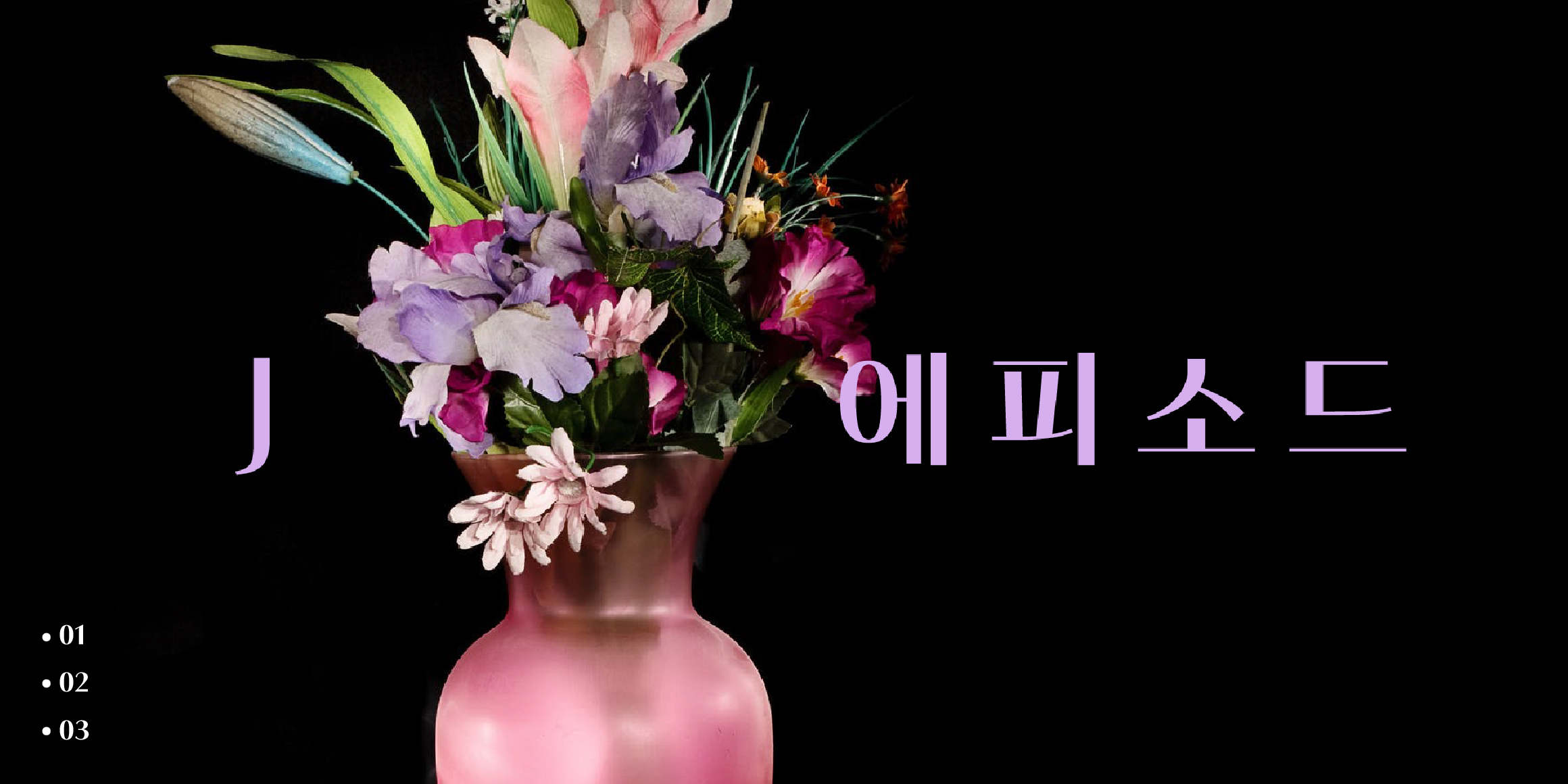
우주와 미래를 그리는 SF 폰트 추천
이번 큐레이션에서는 SF 장르에서 영감을 얻은 폰트들을 소개합니다.
우주 배경, 디지털 인터페이스를 표현할 폰트를 찾는다면 주목해 주세요!
To Infinity and Beyond! 🛸
무한한 공간 저 너머로!
우주와 미래를 다룬 SF 영화나 드라마에서는 미래적인 느낌의 타이포그래피가 중요한데요.
이번 큐레이션에서는 SF 장르에서 영감을 얻은 폰트들을 소개합니다.
우주선 조종실, 디지털 인터페이스, 인공지능의 음성 메시지 자막까지.
레트로 퓨처리즘 분위기를 완성하는 폰트들을 만나보세요!
#01. 우주와 맞닿은 한글
SF 장르에서 자주 보이는 ‘레트로 퓨처리즘’ 감성을 한글로도 표현한다면 어떤 모습일까요? 기계처럼 정밀한 구조와 과거에서 온 듯한 디자인이 공존하는 이 폰트들은, 마치 우주복을 입은 한글처럼 느껴져요. SF 분위기를 연출하고 싶은 포스터나 표지에 사용할 수 있는 이 조합, 꼭 눈여겨보세요!
SD 코스모
• 파란색 우주 배경 위에 네온 사인 효과가 적용된 굵은 한글 타이틀 그래픽: 레트로 퓨처리즘. FONT: SD 코스모
• 파란색 우주 배경의 굵은 텍스트: 코스모스(cosmos) 우주관. FONT: SD 코스모
• 우주 배경 위에 두 단으로 나열된 SF 영화 제목 리스트. 터미네이터, 블레이드러너, 에반게리온, 스타트렉 등. FONT: SD 코스모
「SD 코스모」는 ‘레트로 퓨처리즘’이라는 키워드로 제작된, 이름부터 우주와 맞닿아 있는 폰트입니다. 각진 형태와 대각선으로 커팅된 획이 만들어내는 독특한 구조로 기계적이되 정적인 느낌보다는 역동적인 인상을 가지고 있어요. 특히 오픈타입 피처 기능으로 단어의 첫 자와 마지막 자를 대체하면, 타이틀을 더 매력적으로 디자인할 수 있답니다. 큰 사이즈에서 매력이 더 잘 드러나는 폰트로, 포스터나 오프닝 타이틀용으로 추천합니다!
J에피소드_플래시백
• 달 표면 배경의 텍스트: 암스트롱, FONT: J에피소드 플래시백
• 달 표면 배경의 영문 텍스트: 암스트롱의 달 착륙 관련 인용구. FONT: J에피소드 플래시백
• 검은 배경과 녹색 달 그래픽 위에 배치된 폰트 적용 예시. J에피소드 플래시백 02, 03 서체 비교 예시
「J에피소드_플래시백」은 직지소프트의 J에피소드 패밀리의 두 번째 시리즈 폰트입니다. 기존 J에피소드 시리즈의 느낌을 이어가되, ‘과거와 맞닿은 미래’라는 컨셉 아래 획 대비를 반전시켜 완전히 상반된 인상을 보여줍니다. 반전된 획이 만들어내는 묘한 이질감이 SF 장르의 감성을 한층 살려주죠. 아날로그한 감성을 입힌 미래 배경이나 주제와 관련된 디자인에 에피소드 플래시백을 활용해 보세요!
HG코스모스
어두운 우주 배경에 붉은색 굵은 강조된 텍스트: 공간의 광막함과 시간의 영겁에서. FONT: HG코스모스
미래적인 분위기는 이런 디테일에서 나오는 걸까요? 역획대비(reverse-contrast)가 특징인 또 다른 디스플레이 폰트, 「HG코스모스」 입니다. 기본 구조와 형태는 꽉찬 네모꼴의 단단한 모듈을 가지고 있지만, 가로획과 세로획의 두께만 바꿔도 새로운 공간과 인상이 드러나죠. 직선적인 형태의 A 스타일과 곡선적인 형태의 B 스타일로 구성되어 있어, 차가움과 유려함 사이에서 원하는 스타일을 골라 사용해 보세요!
#02. 감각적인 미래의 언어
이번에는 SF 영화에서 자주 본 듯한 느낌의 영문 폰트들을 소개할게요. 어디선가 신비로운 빛을 내며 우주선 문이 열리면 등장할 것 같은 글자들이죠. 디지털 화면 위의 글자 같기도, 외계 생명체의 언어 같기도 한 이 폰트들만 있다면 SF 무드 완성은 시간 문제죠!
ABC Pareto
• Dinamo ABC Pareto 텍스트 그래픽, 전시 브로슈어와 엽서 목업 이미지 - 01
• Dinamo ABC Pareto 텍스트 그래픽, 전시 브로슈어와 엽서 목업 이미지 - 02
• Dinamo ABC Pareto 텍스트 그래픽, 전시 브로슈어와 엽서 목업 이미지 - 03
「ABC Pareto」는 이름만큼이나 다채로운 매력을 가진 폰트예요. 획 끝의 형태가 원형, 삼각형, 직사각형—세 가지 도형을 오가며 짜여진 글자로 독특한 성격을 자아냅니다. 마치 우주선이나 로켓의 일부분처럼 보이지 않나요? 폰트 하나만으로도 다양한 스타일을 표현할 수 있어서, 장면 전환이 많거나 복합적인 장르의 SF 콘텐츠에서 효과적으로 쓸 수 있어요!
TT Paplane Basic
TT Paplane 폰트의 적용 예시. 종이접기처럼 각진 형태의 알파벳, 숫자, 특수기호 디자인
「TT Paplane」은 종이비행기를 접어 만든 듯한, “paper plane”에서 이름을 따온 폰트예요. 종이처럼 평평하고 대비가 적은 Regular 스타일과, 독특한 역획대비가 적용된 Thin 2가지 스타일로 구성되어 있는데요. 특히 Thin은 영문 대문자가 소문자보다 확연히 좁은 비율로 구성되어 있어 인위적이고 기계적인 느낌을 살린 영상 자막이나 미래적인 디자인의 포스터에 활용하기 좋아요. 미디어아트 축제 <서울라이트 DDP 2025 여름> 포스터에 사용된 모습도 확인해보세요! (링크)
Bill Display
삼각형 도형을 기본으로 디자인된 기하학적 폰트 Bill Display 적용 예시
맥스 빌(Max Bill)의 레터링 작업을 기반으로 한 이 폰트는, 미니멀한 요소를 엣지 있게 활용한 「Bill Display」입니다. 트렌드를 따르기보다는, 시대를 초월하는 어휘를 구현하고자 한 폰트로 과거와 미래를 넘나드는 SF 장르에 아주 잘 어울리죠. 영문 대문자와 소문자 스타일이 분리되어 있어 원하는 형태를 골라 쓸 수도 있어요. 영화 오프닝 타이틀, 전시 포스터, 모션 그래픽 타이포그래피 등 미니멀한 무드가 필요한 프로젝트 어디든 효과적으로 활용해 보세요!
#03. 0과 1의 세계로
이 폰트들을 보고 있으면 마치 0과 1이 흘러다니는 데이터 세계에 들어온 듯한 느낌이에요. 픽셀이나 격자, 컬러로 디자인된 요소들 덕분에 보는 순간 배경이 ‘디지털’ 느낌으로 전환되죠. 고도로 발전한 미래의 기술이나 그래픽을 시각적으로 보여주고 싶을 때, 이 폰트만 사용해서 작업 시간까지 단축해보세요!
Shader color
레트로 게임 느낌의 픽셀 아트 스타일 이미지. FONT: Shader Color
「Shader Color」는 이미지처럼 컬러나 픽셀 요소가 질감으로 입혀진 폰트입니다. 16비트 게임에서 튀어나온 듯한 픽셀 스타일, 반짝이는 64비트의 컬러 폰트, 그리고 의도적으로 오류처럼 보이도록 디자인된 글리치 스타일까지. 컬러 폰트를 지원하는 환경이라면 어디서든 감각적인 디자인에 활용해 보세요! 게임 UI, 그래픽 영상, 타이틀 로고까지 SF 장르의 감각을 시각적으로 전달할 최적의 폰트로 추천합니다. 컬러가 없는 기본 스타일도 제공하니 아래 「Shader」 폰트 페이지에서 만나보세요.
로제타타입
Gridlite PE
도트 패턴과 선으로 구성된 실험적인 텍스트 그래픽. FONT: Gridlite PE
「Gridlite」는 그리드와 음영을 실험적으로 적용한 모노스페이스 배리어블 폰트입니다. 글자 사이와 배경의 공간들까지 모듈화했다는 점이 독특한데요. 배리어블 기술의 끝을 보여주는 듯, 슬라이더를 움직일 때마다 달라지는 형태를 보는 재미가 있으니 꼭 사이트(링크)에서 테스트 해보세요! 이렇게 타이포의 스케일 변화와 애니메이션에 최적화되어 있어, 동적인 인터페이스나 타이포그래피 비디오 작업에 추천합니다.
라인투
Moonbase
둥근 픽셀 폰트 Moonbase 적용 예시
마지막으로 소개할 폰트는 라인투의 「Moonbase」입니다. 「Moonbase」는 1991년 탄생한 실험적인 픽셀 폰트 ‘Moonbase Alpha’를 기반으로, 현대적으로 재해석한 디스플레이 폰트예요. 저사양의 픽셀화된 화면의 글꼴을 의도적으로 가져와서, 조잡한 픽셀 모양을 다듬고 모서리를 둥글게 굴려서 완성된 이 폰트는 초기 사이버 문화와 디지털 DNA를 그대로 지니고 있어요. ‘Moonbase Alpha’는 NASA의 2021년 화성 탐사 프로젝트 엠블럼에도 사용되었을 정도로, 이미 SF 장르와 어울리는 구조를 타고났죠. 픽셀, 레트로, 디지털 요소를 타이포그래피로 표현하고 싶을 때 딱 어울리는 폰트로 추천합니다!
SF 장르는 단순히 ‘미래’를 이야기하는 게 아니에요. 때로는 지금보다 더 감정적인 세계를 상상하고, 기술과 인간의 경계를 흐리기도 하죠. 이번에 소개한 폰트들은 그런 복잡하고 흥미로운 SF의 분위기를 텍스트만으로도 충분히 전달할 수 있는 폰트들이에요. 어떤 우주의 이야기든, 거기엔 그 세계만의 언어가 필요하니까요. 👽